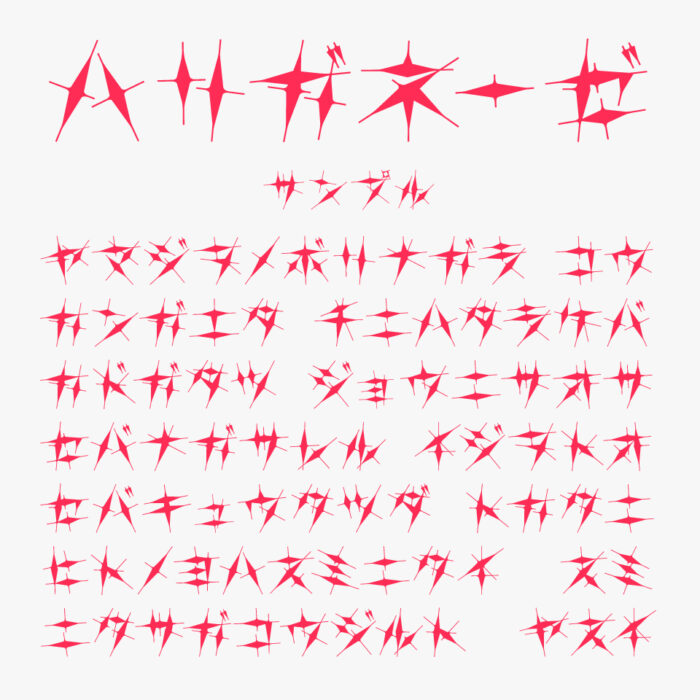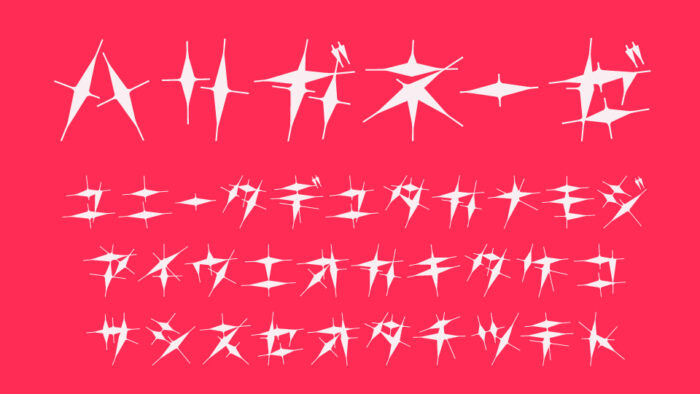
ハリガネーゼフォントは、針金細工のように細く尖った線が交差し、星型の輝きを思わせるフォルムが特徴のアート系デザインフォントです。
文字というよりも装飾的なアートのような文字ですが、視覚的に非常にユニークで個性的な存在感がありとっても素敵です。
可読性は低くなってしまいますが、その分、強い印象とインパクトを与えるので、目を引くタイトルやロゴなどに取り入れてみると良さそうです。
収録文字は、カタカナ・一部記号が収録されています。
| ひらがな | × |